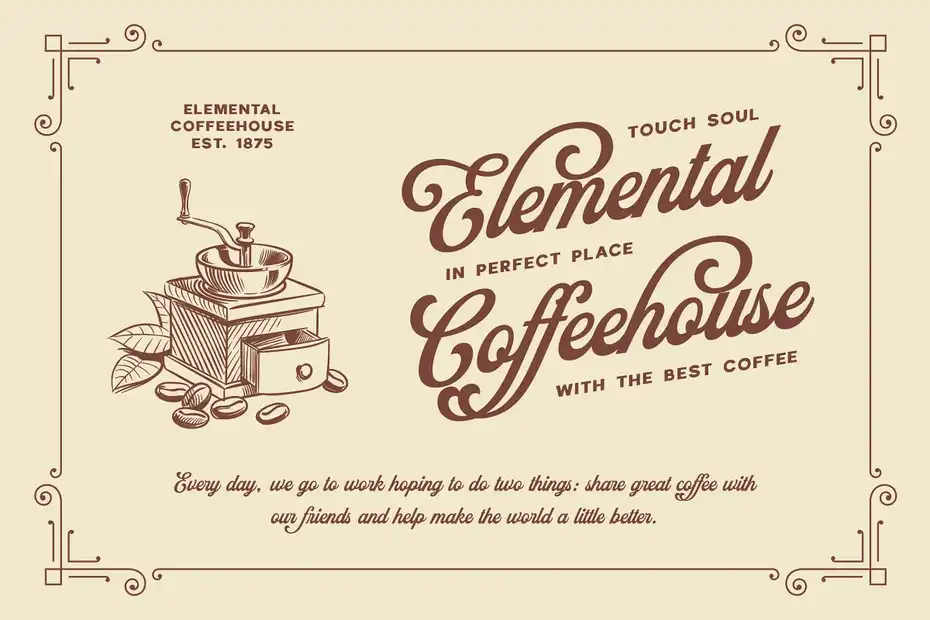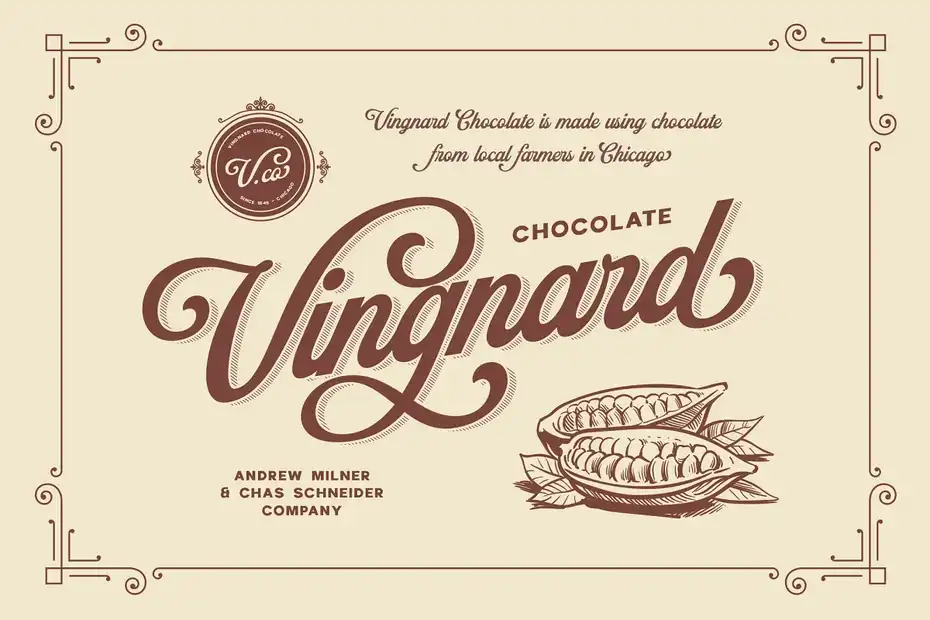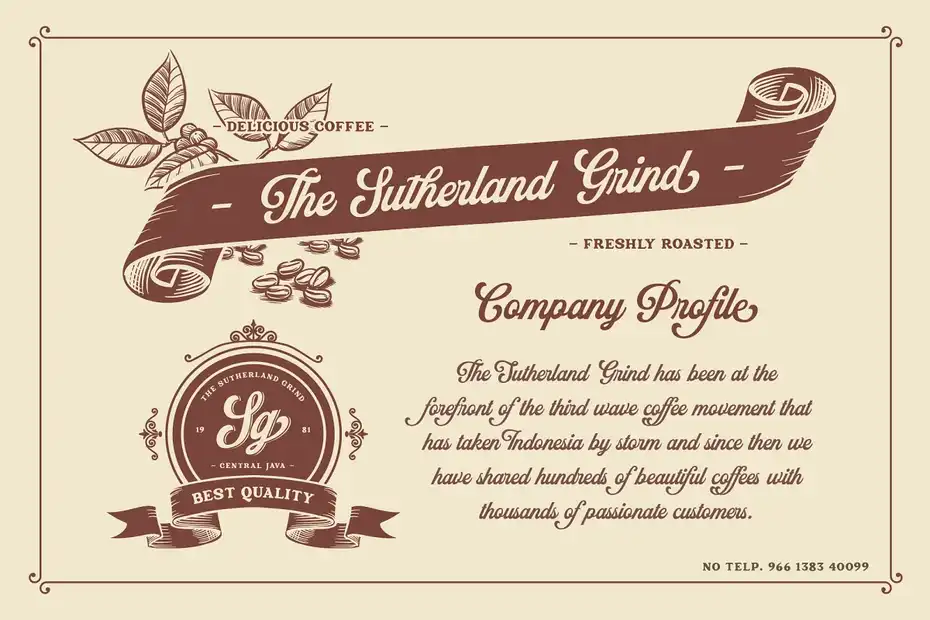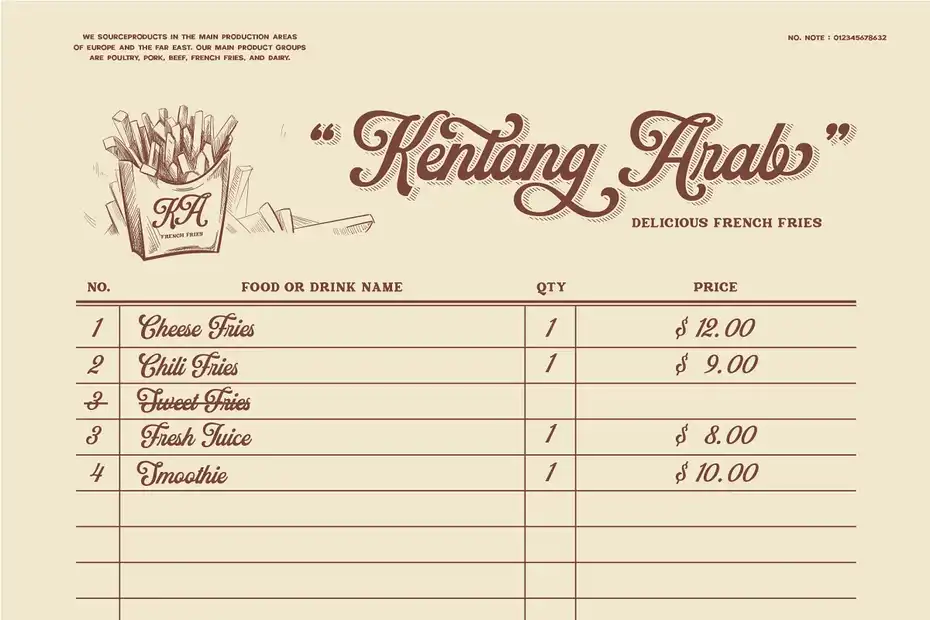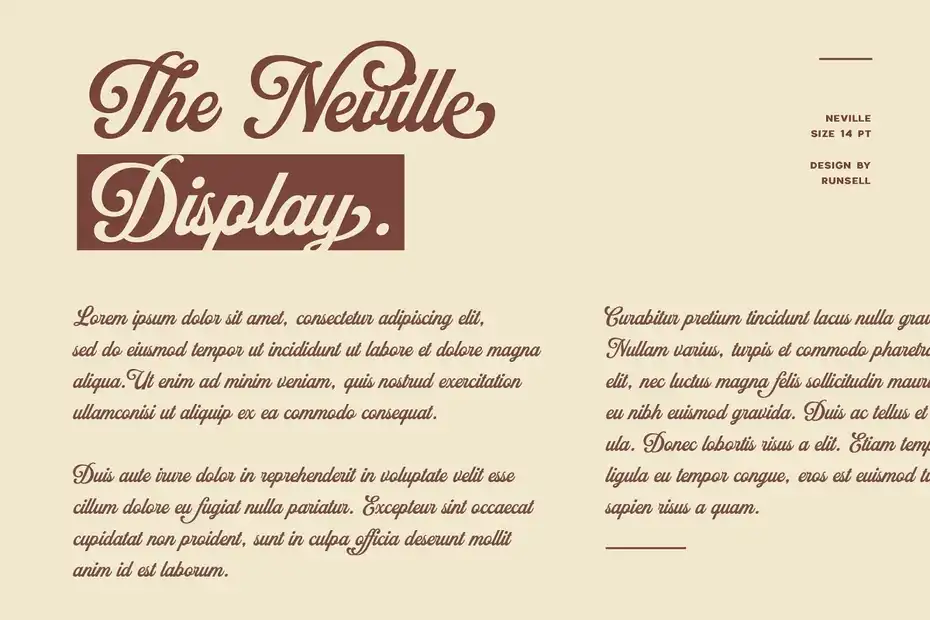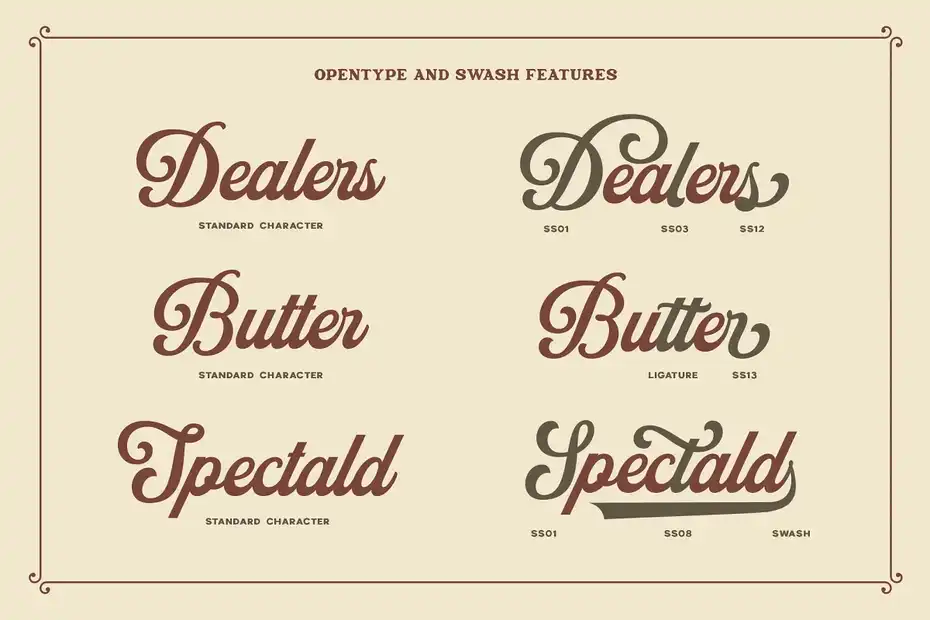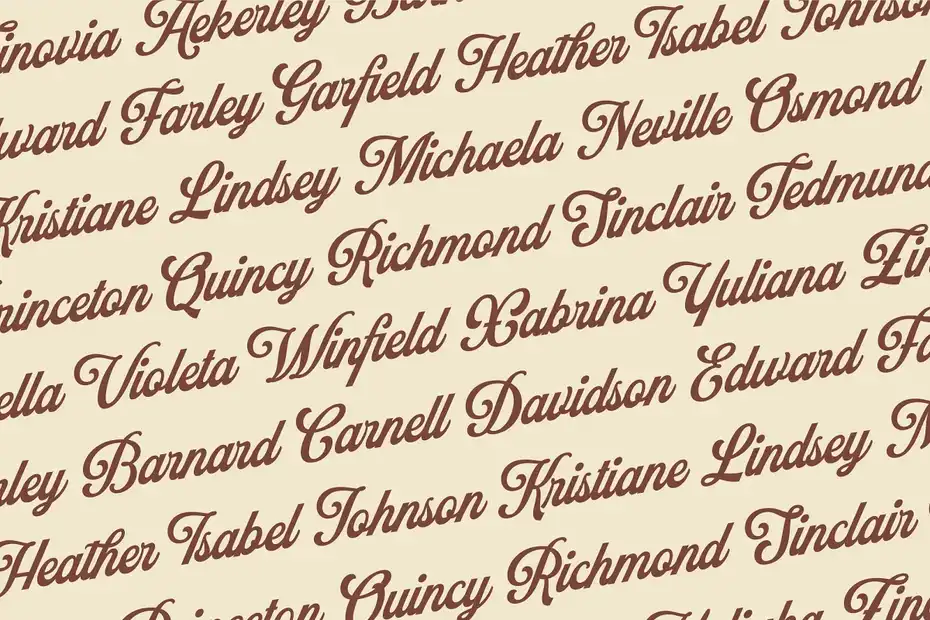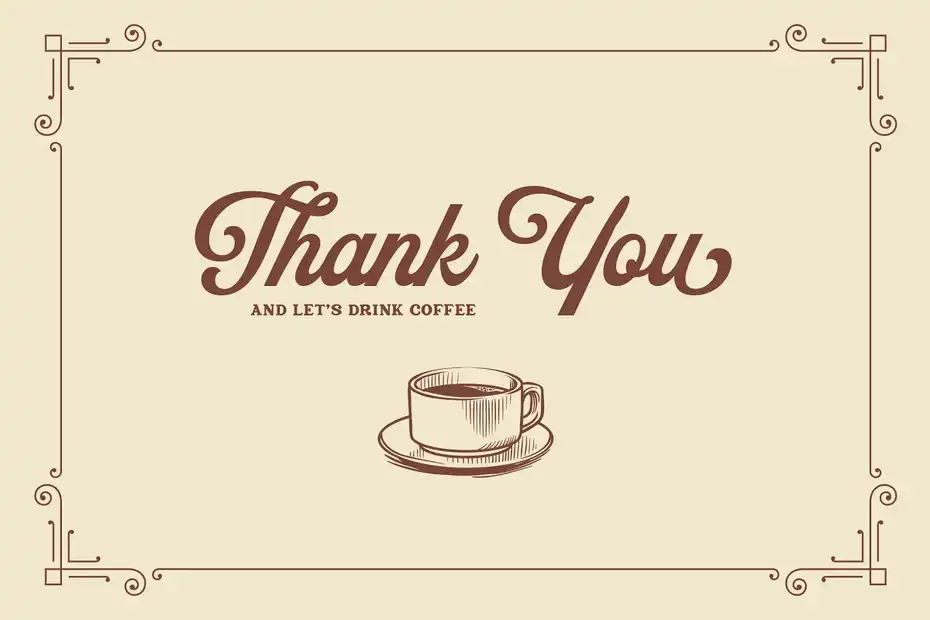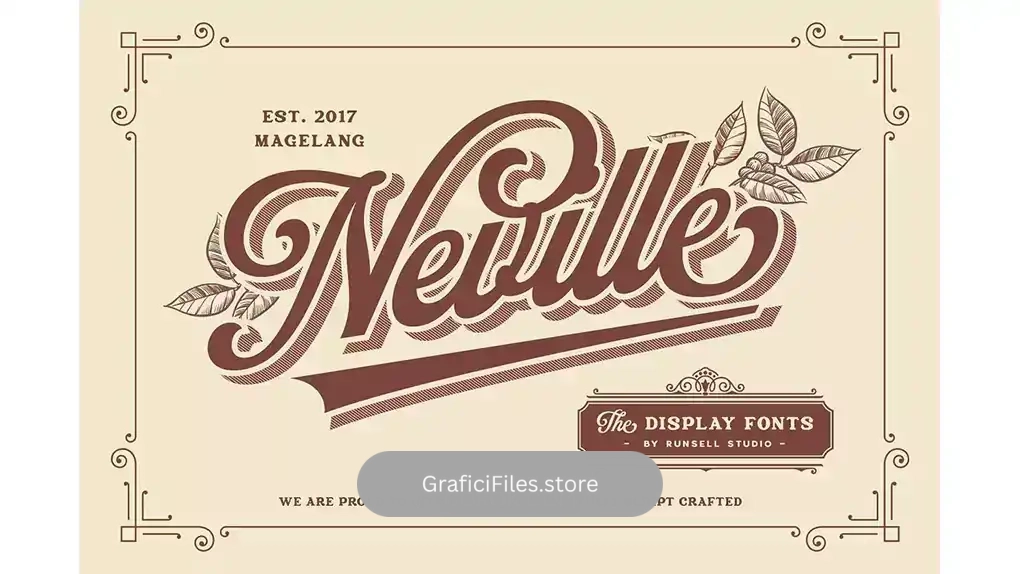
دانلود فونت انگلیسی کلاسیک Neville Font
فونت انگلیسی کلاسیک Neville Font : این مجموعه شامل یک فونت انگلیسی کلاسیک است که برای لوگو، برندینگ، نقل قول، کارت ویزیت و غیره مناسب میباشد.
• عنوان مجموعه: Neville Font